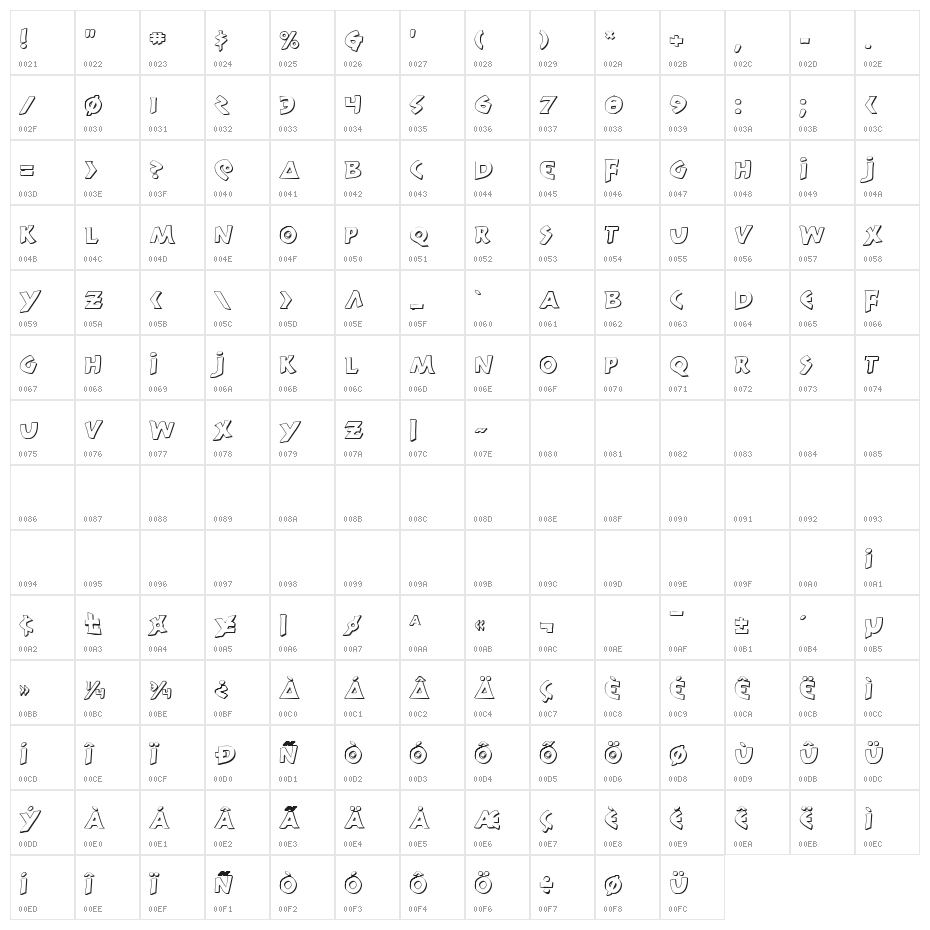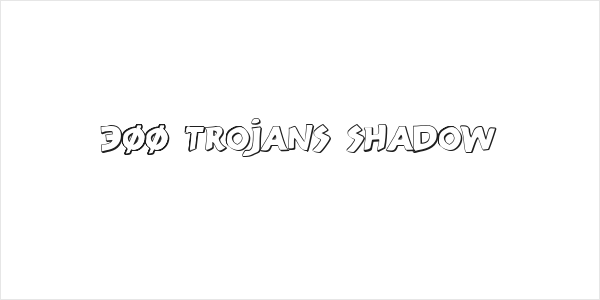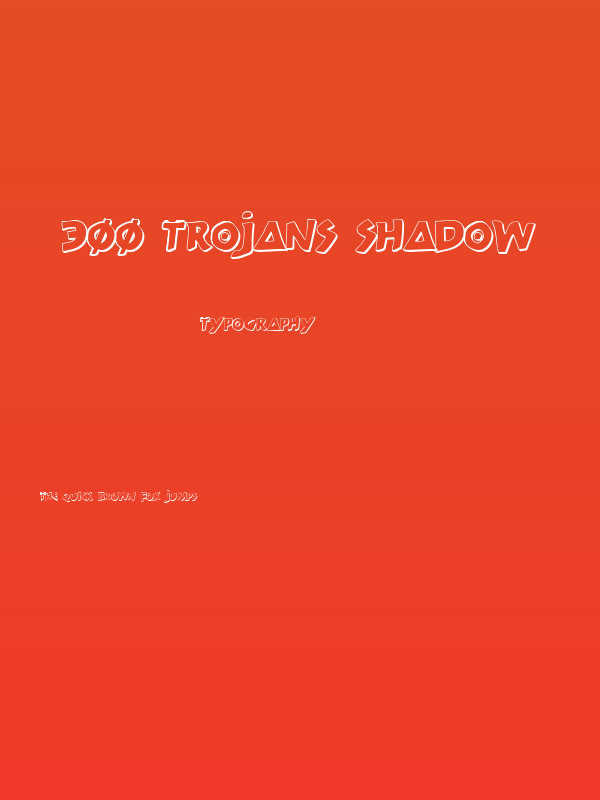
300 Trojans Shadow Font
| 推荐项目 | Ideal for comic book titles, posters, video game graphics, and any project needing a bold, playful touch. |
300 Trojans Shadow